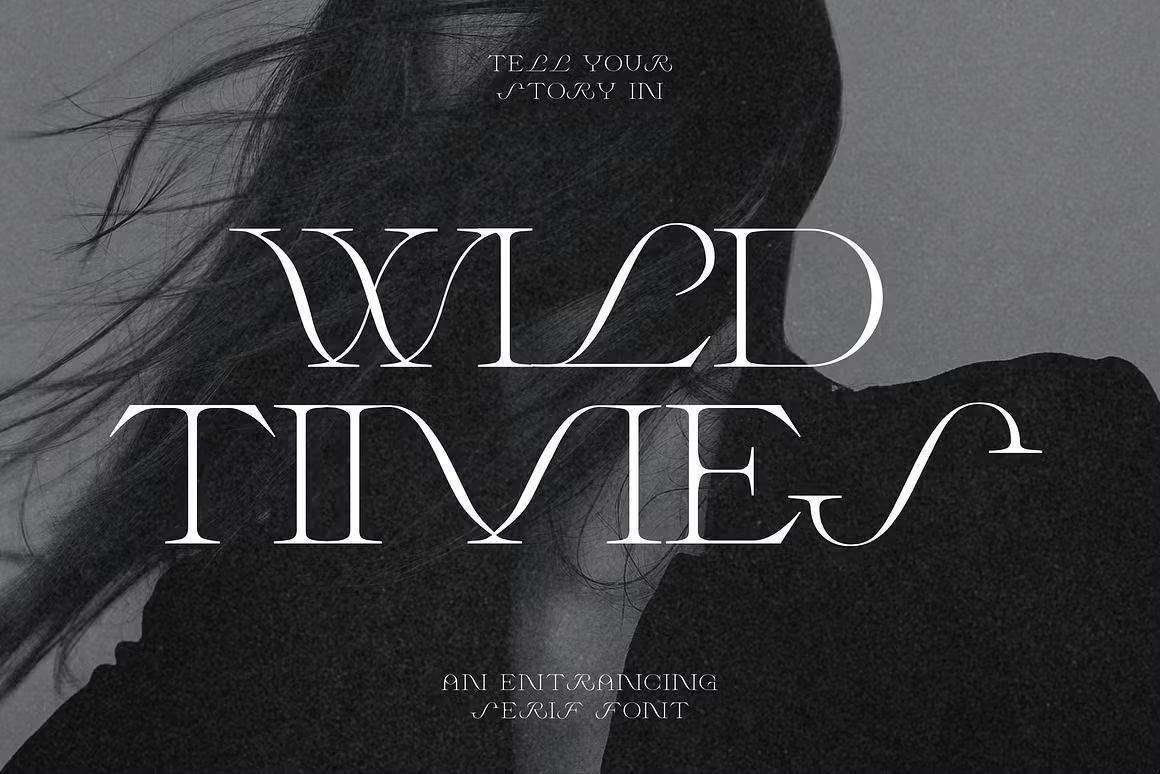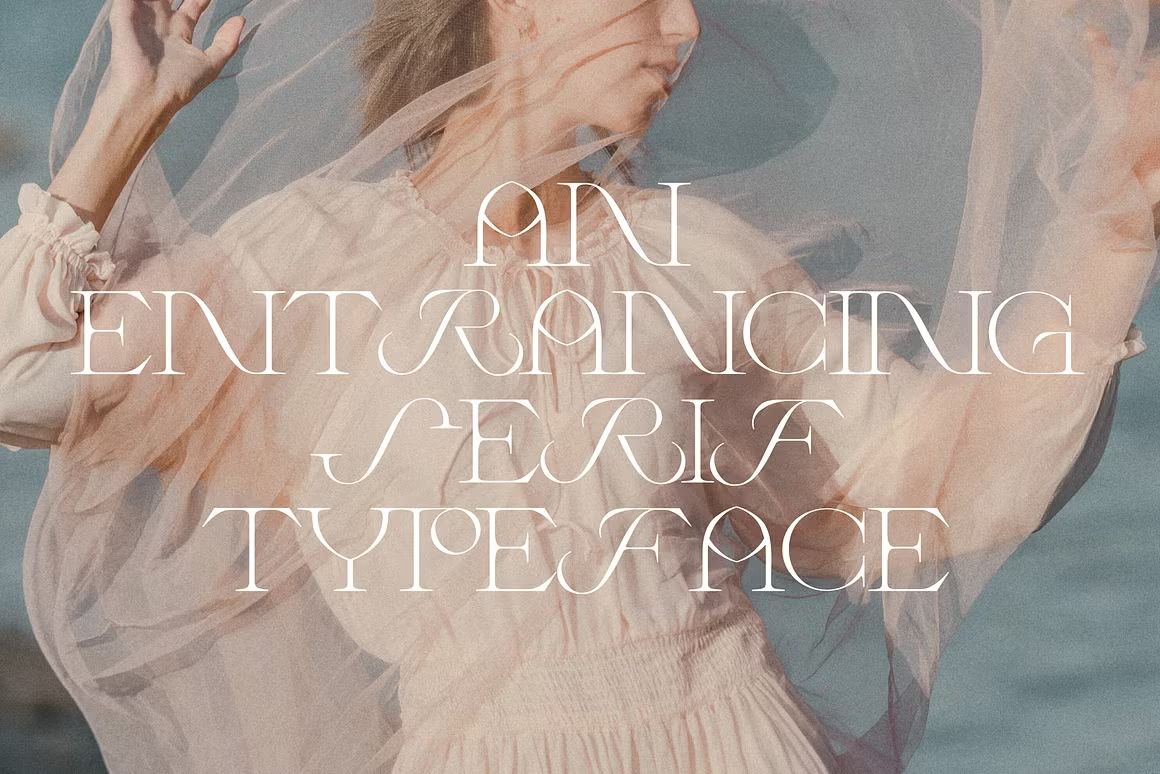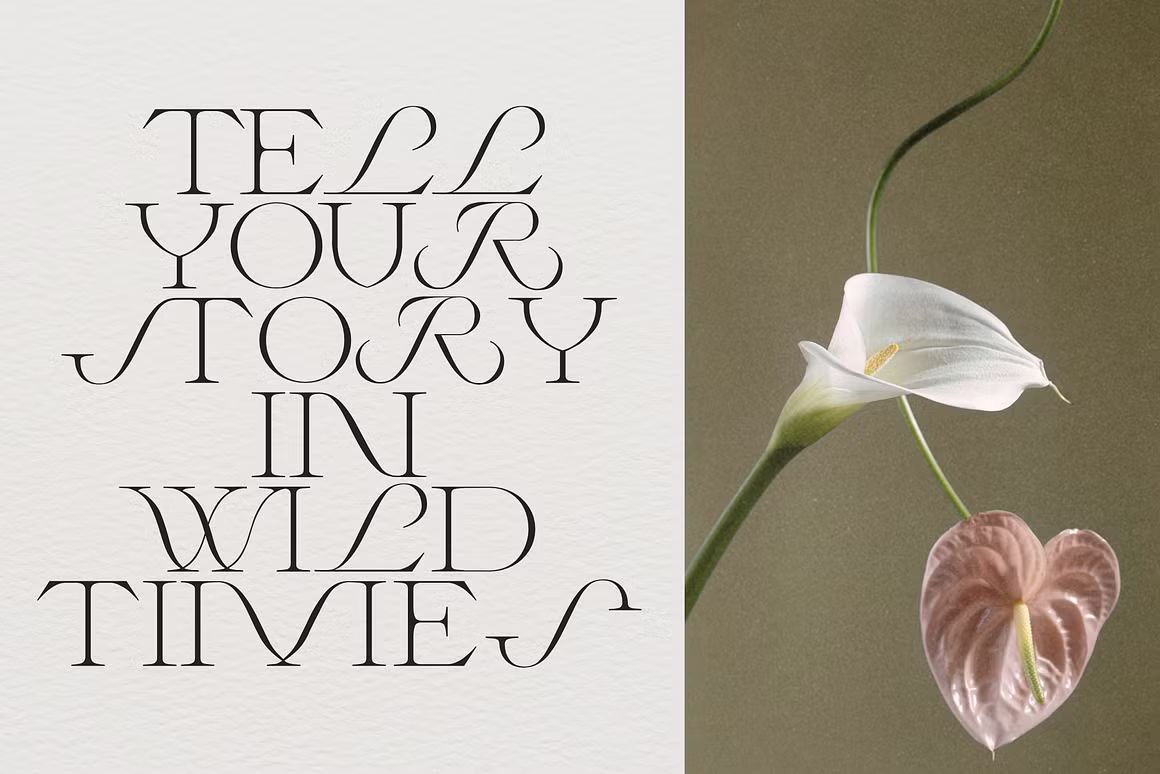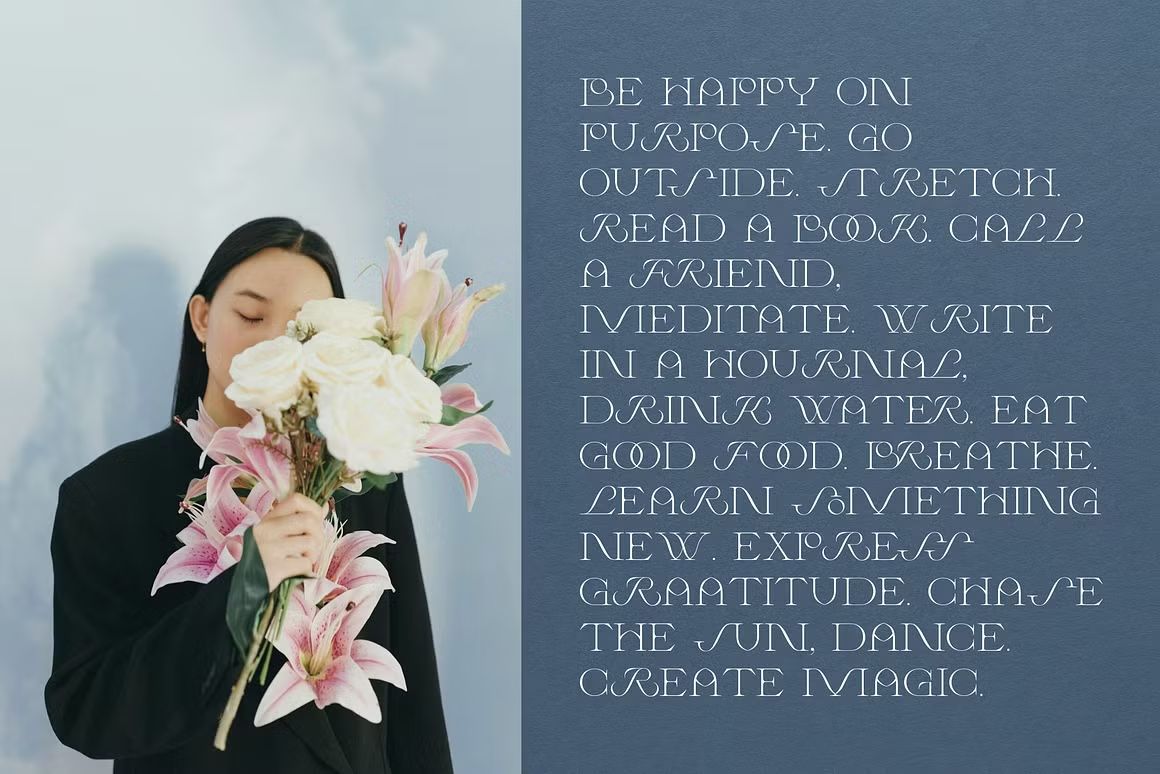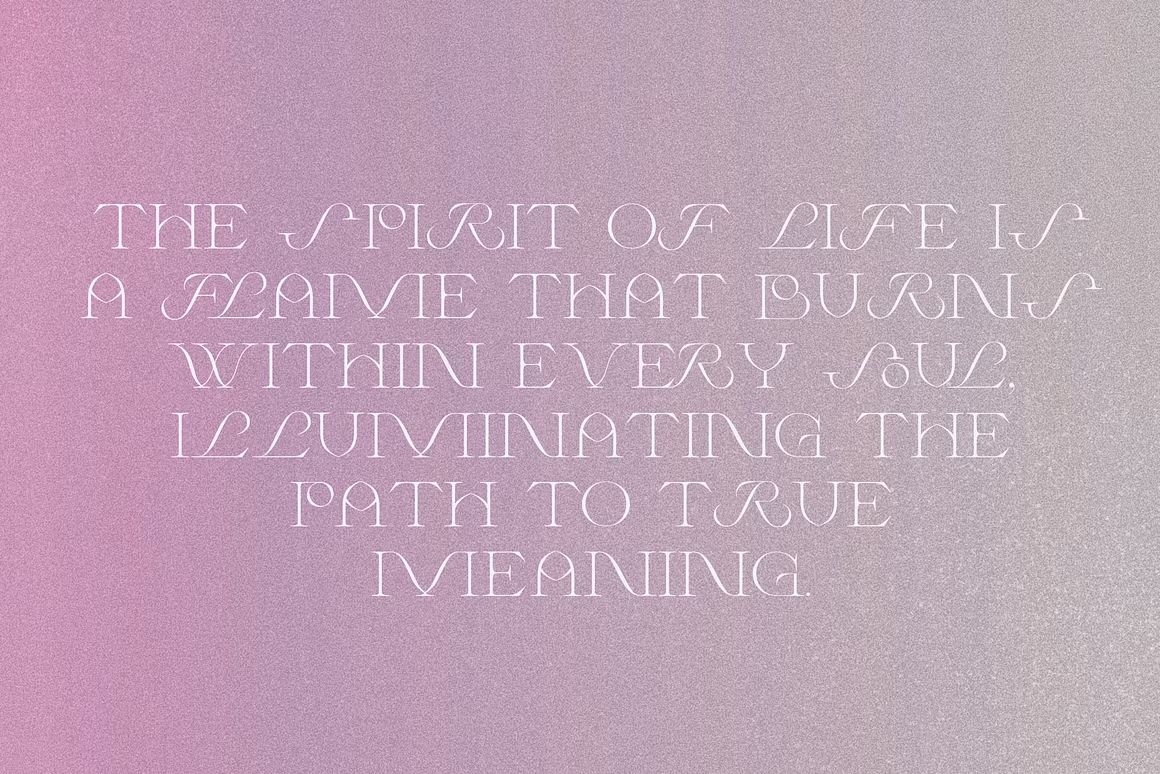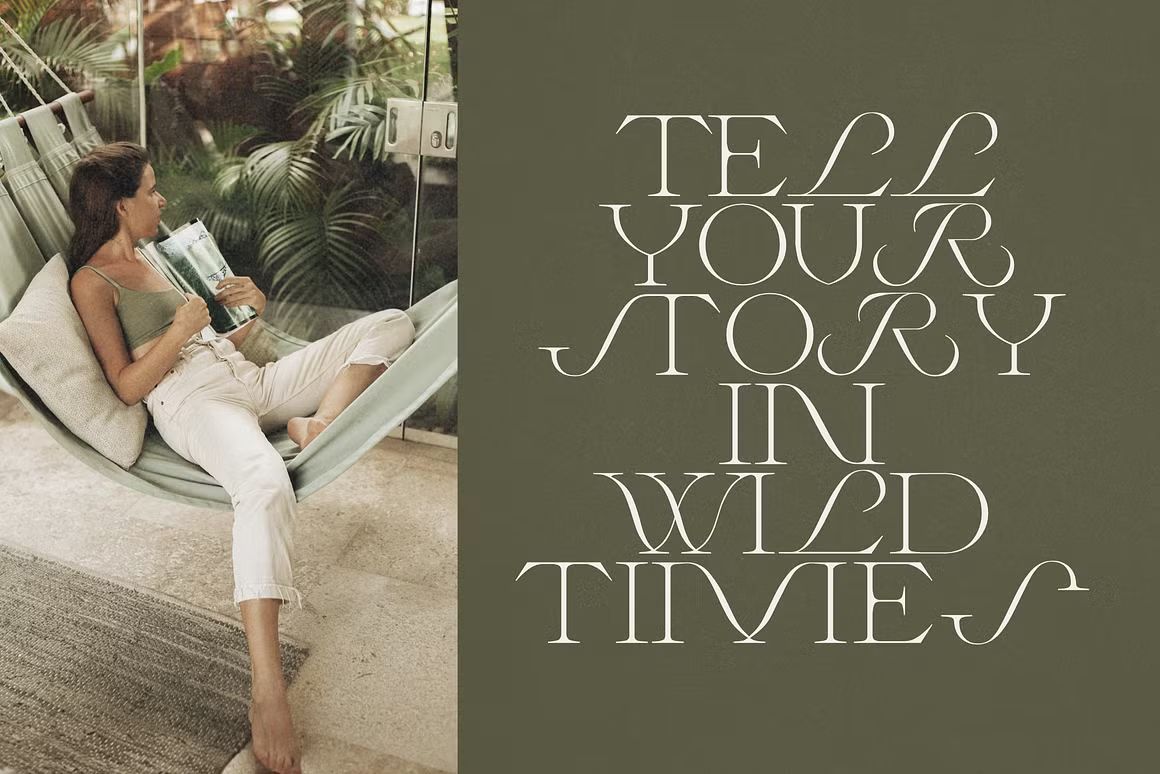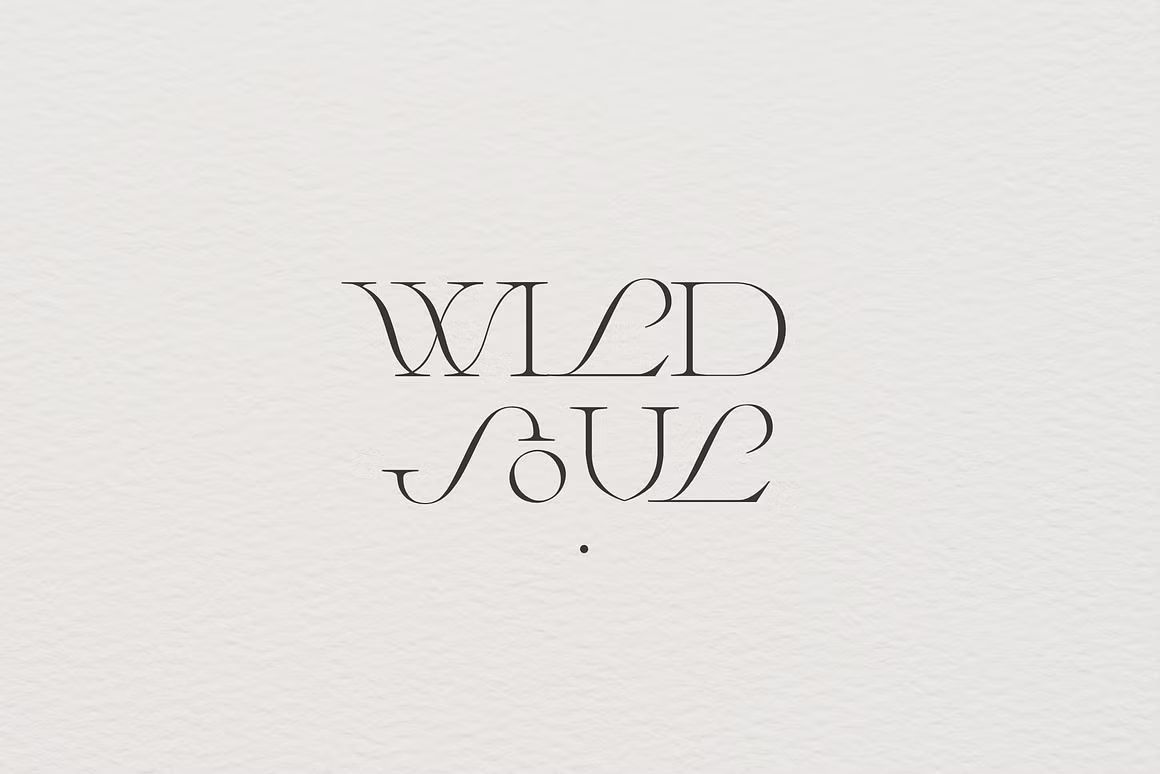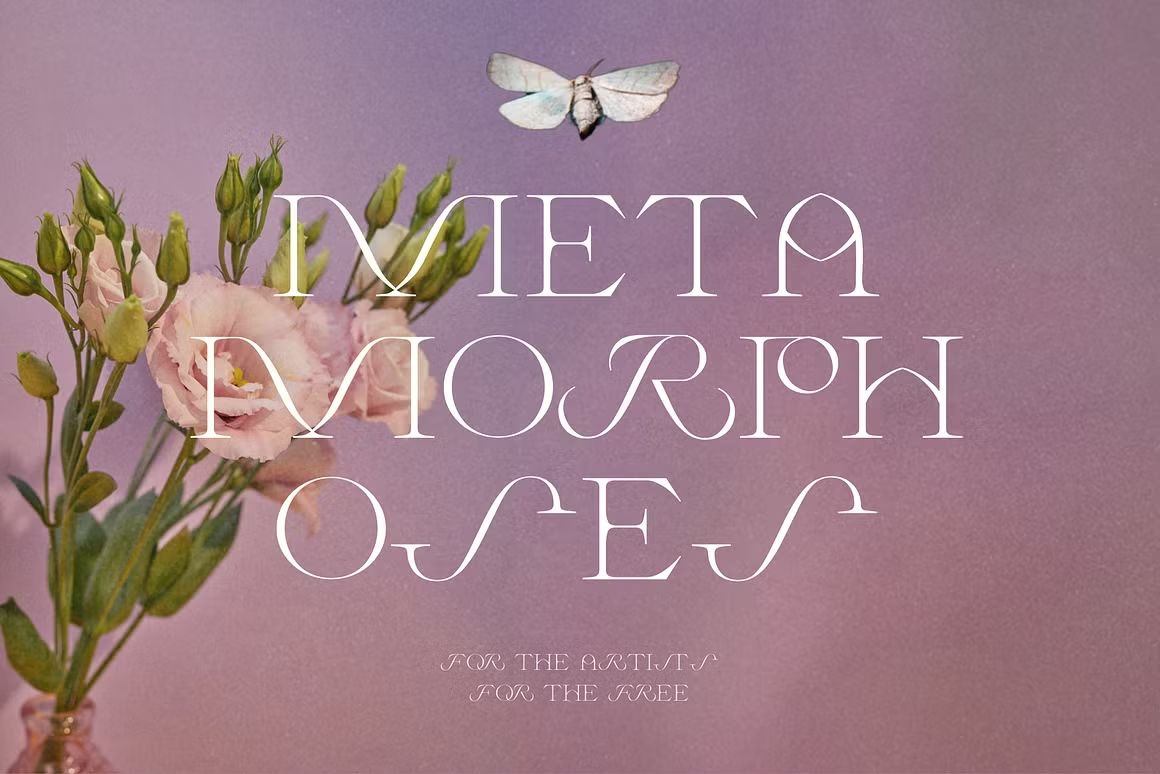
Wild Times – Serif Font
Wild Times adalah font serif dengan gaya bold dan tegas yang menghadirkan kesan klasik, elegan, dan sedikit vintage—cocok untuk branding, editorial, poster, dan proyek desain yang ingin tampil berkarakter.
Wild Times adalah font serif yang menggabungkan gaya klasik dengan sentuhan bold yang kuat dan elegan. Dengan karakter yang berani dan sedikit nuansa vintage, font ini ideal untuk digunakan dalam branding, editorial, poster, kemasan, dan proyek desain lain yang membutuhkan tampilan yang mencolok namun tetap berkelas.
Fitur unggulan:
• Gaya serif bold dengan nuansa klasik dan vintage
• Cocok untuk branding, editorial, poster, dan desain kemasan
• Termasuk huruf besar, huruf kecil, angka, dan simbol lengkap
• Ideal untuk proyek cetak maupun digital dengan tampilan elegan dan berkarakter